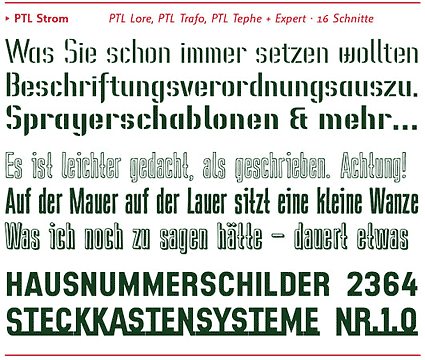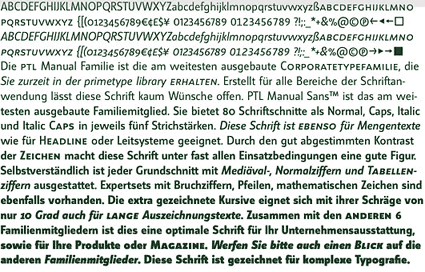
Neu im Programm: Primetype-SchriftenBerlin. Ab sofort vertreibt FontShop die Schriften der auf Corporate- und
Editorial-Typography spezialisierten Berliner Primetype GmbH.
Neben großen Textfamilien gehören auch sympathische Display-Revivals
aus DDR-Zeiten zum Repertoire des jungen
Schriftenhauses.
![]() Ob im Corporate Design, bei der Gestaltung einer Zeitschrift
oder dem Entwurf eines Plakats: die Schriften von Primetype bieten alle
typografischen Voraussetzungen. Neben sorgfältig abgestimmter
Strichstärken zeichnen sich die Familien durch Expertsets,
verschiedene Ziffernsätze und viele
Auszeichnungsmöglichkeiten aus.
¶ Stichwort EU-Erweiterung: Für die Korrespondenzschriften PTL Manual Office und Mono sind osteuropäische Sprachen keine Hürde, denn sie sind unter anderem als OpenType Multilingual erhältlich. Alle Schriften sind für Mac und PC als PostScript und OpenType lieferbar, für den PC zusätzlich in TrueType. Die Großfamilie Manual bietet jede Menge Strichstärken und Auszeichnungsmöglichkeiten: ![]() Das Paket PTL Strom greift historische Industrieschriften aus Ost und West auf und rettet sie vor dem Aussterben: ![]() Herausgegeben: Fr - März 5, 2004 at 03:15 nachm. | |